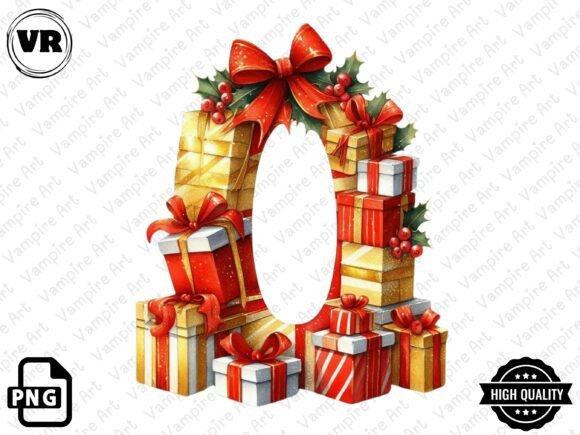
Holiday Typeface and Number Clipart PNG
การค้นหาองค์ประกอบการออกแบบที่เหมาะสมอาจเป็นเรื่องท้าทาย แต่ Holiday Typeface and Number Clipart PNG นำเสนอคอลเลกชันที่โดดเด่นซึ่งช่วยยกระดับงานของคุณได้ทันที
ไม่ว่าคุณจะสร้างผลิตภัณฑ์ POD (Print on Demand) คำเชิญงานแต่งงาน หรือกราฟิกโซเชียลมีเดีย Holiday Typeface and Number Clipart PNG ก็เหมาะสมอย่างยิ่ง